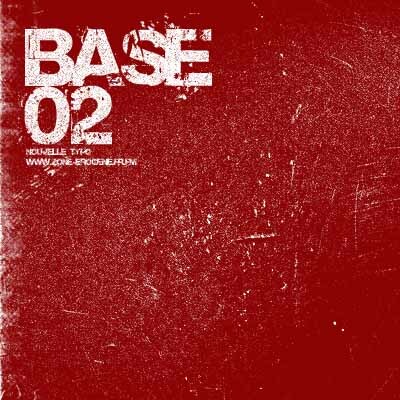
Base 02 di Zone Erogene è un carattere display gratuito e distorto, che sembra quasi trascinato sul cemento e schizzato d'inchiostro. Le lettere massicce e audaci sono erose da granelli e graffi, conferendo a ogni parola un aspetto urbano e rumoroso. È un carattere crudo e tattile, come se fosse stato stampato con stencil usurati e sovra-stampato fino a far rompere la texture.
Con Base 02 puoi portare poster, copertine di album, volantini, zine, titoli di giochi e il branding horror o sci-fi in una modalità caos totale, senza bisogno di texture aggiuntive. Questo font gratuito dà il meglio di sé nelle grandi dimensioni, dove le forme fratturate e gli spazi grunge possono davvero respirare; abbinalo a un carattere sans serif geometrico e pulito per il testo principale, così da mantenere la leggibilità mentre il titolo attira tutta l'attenzione.